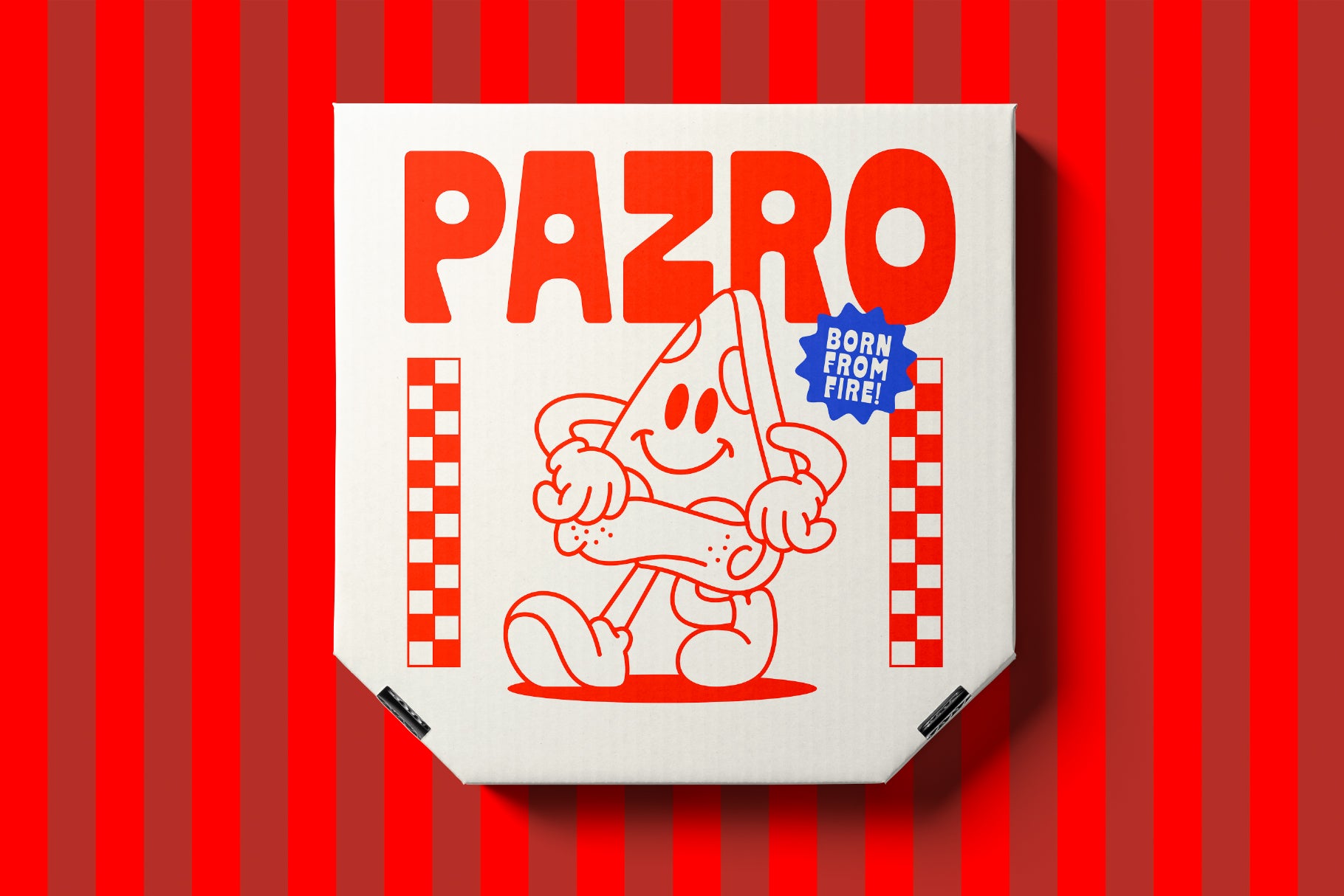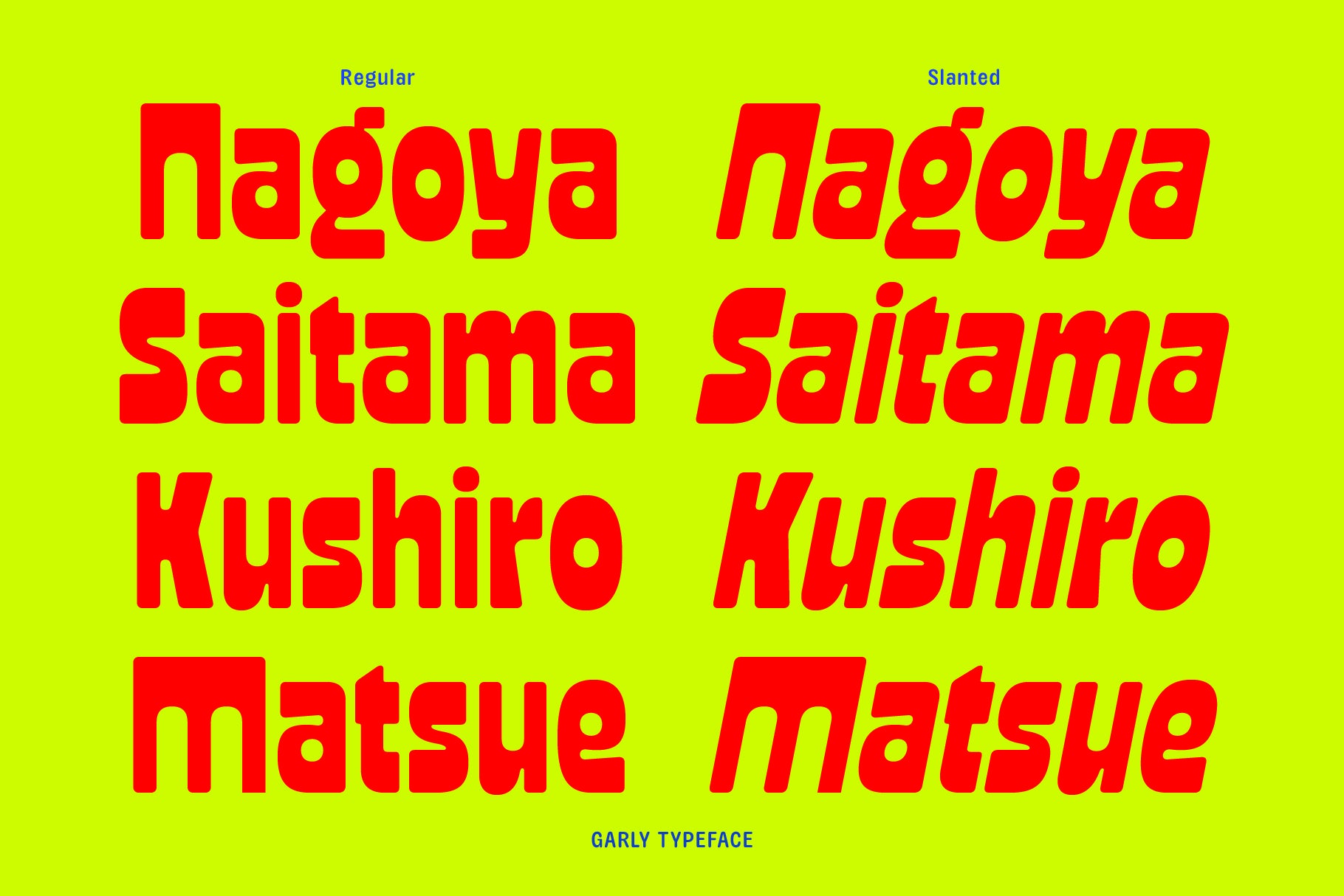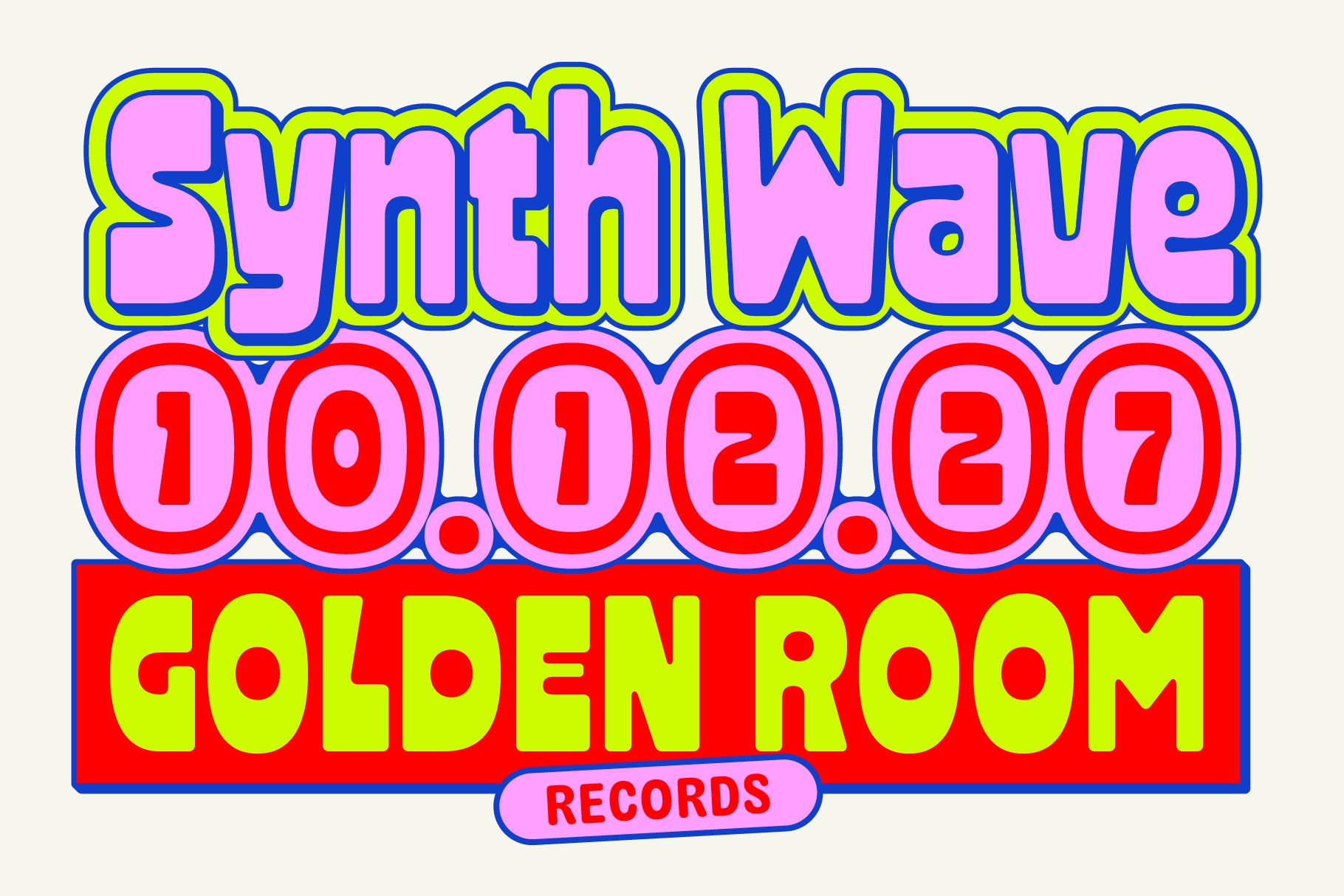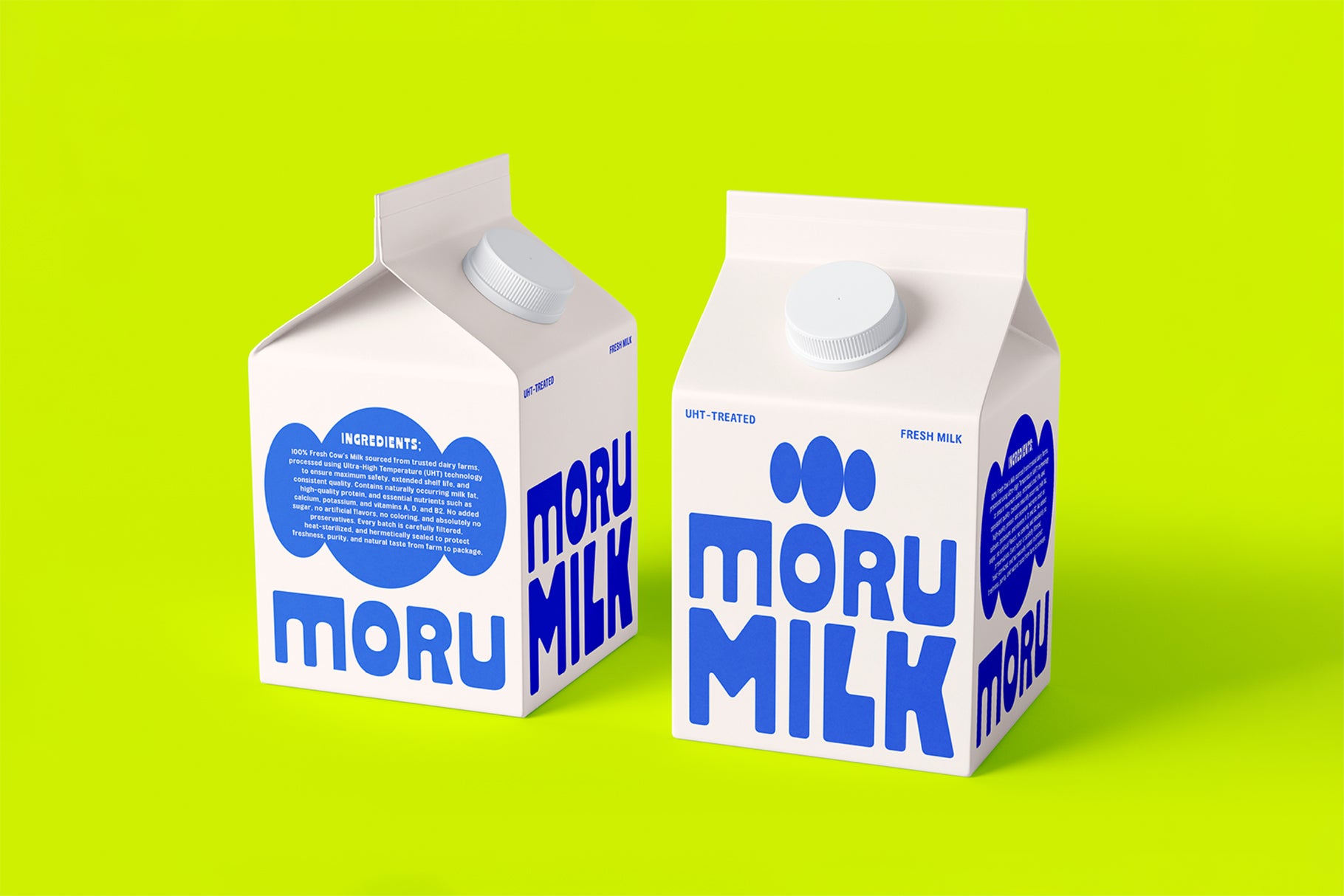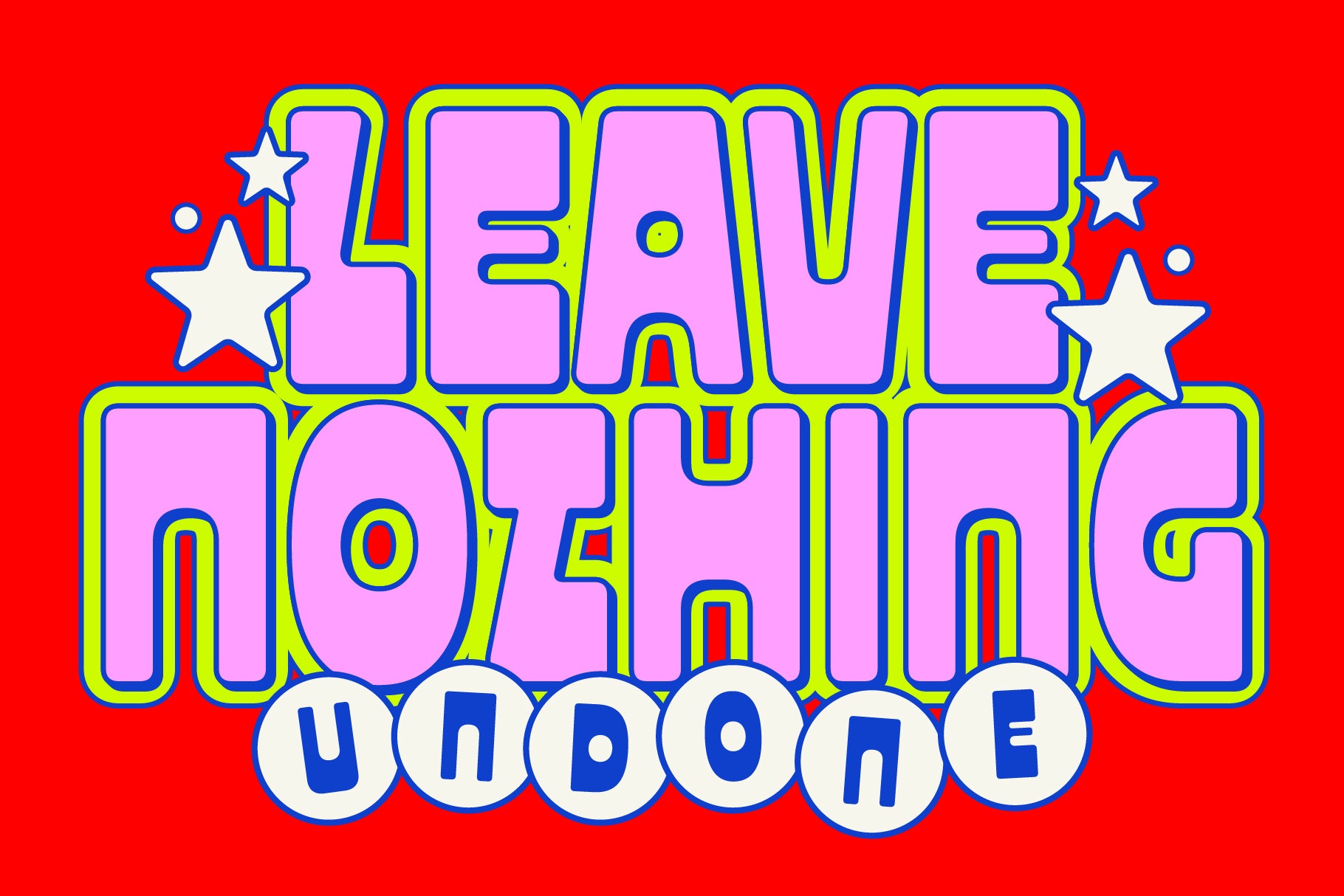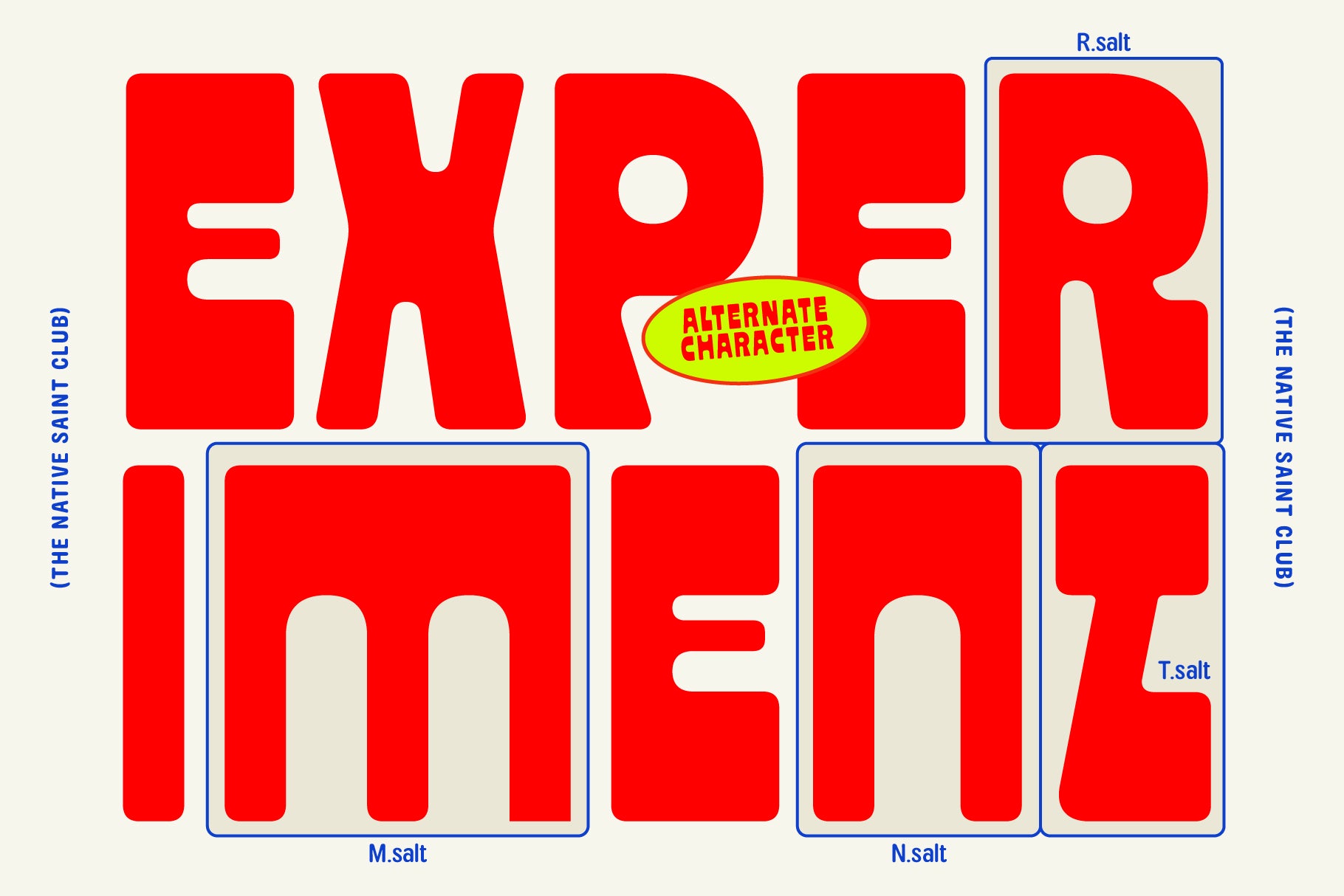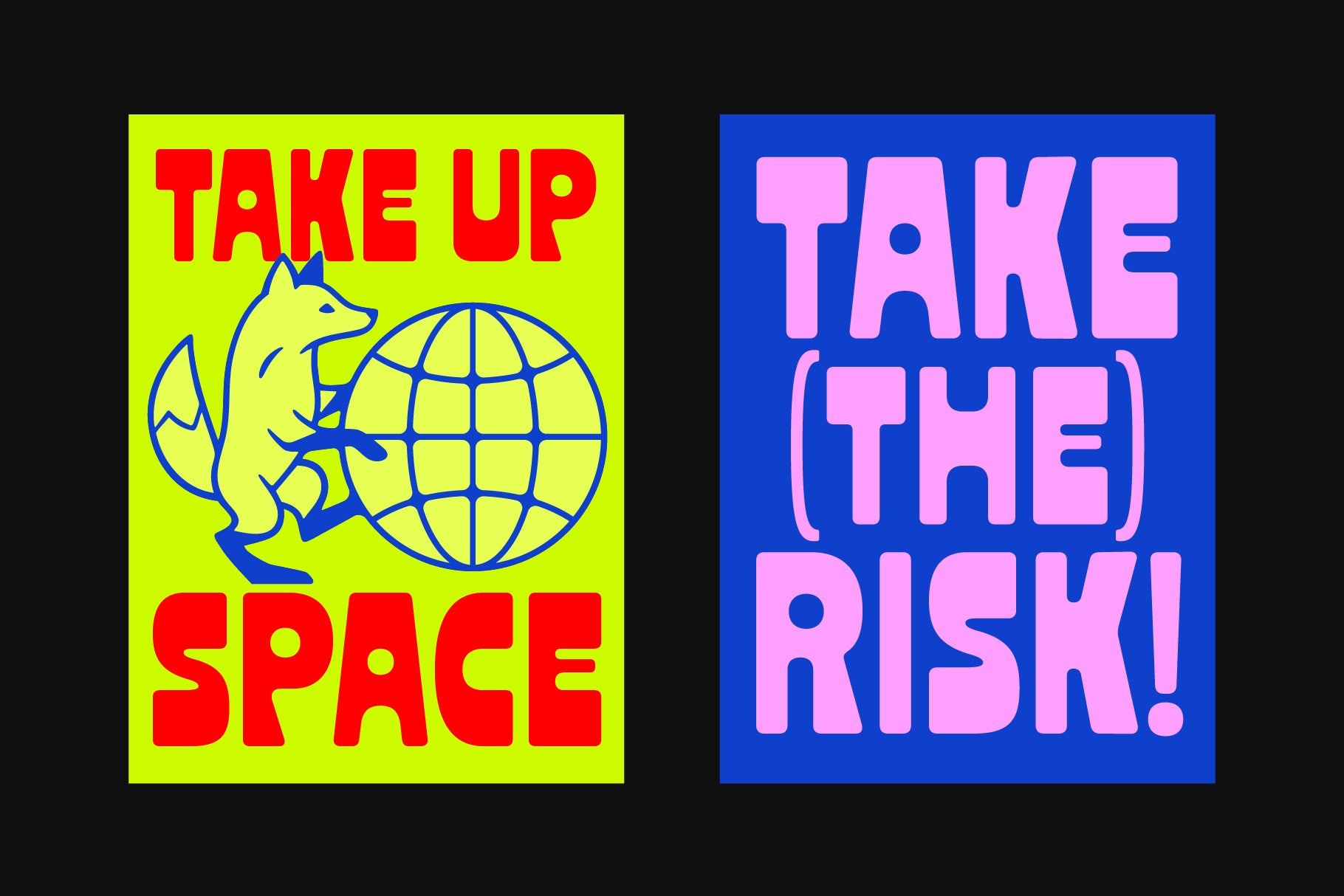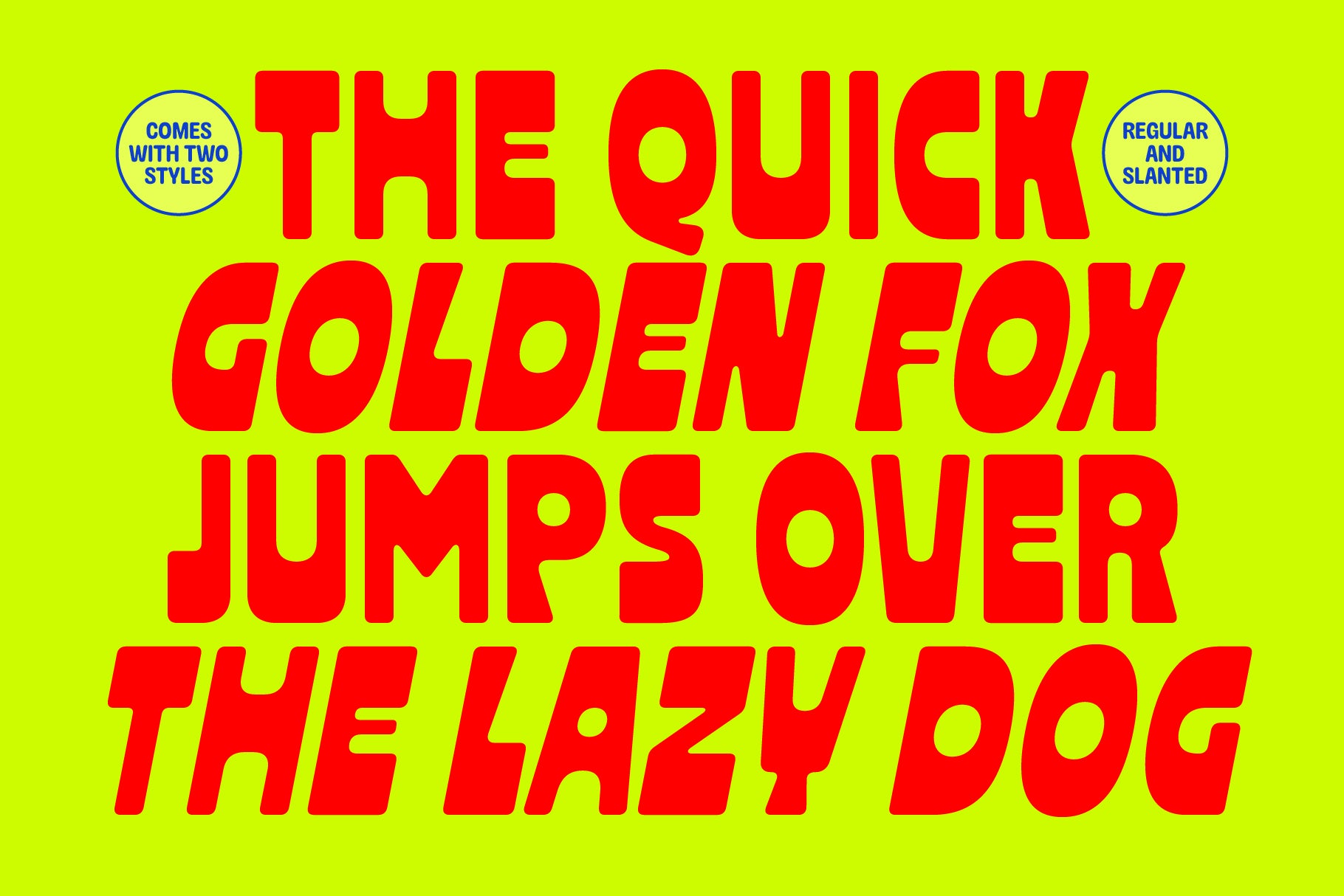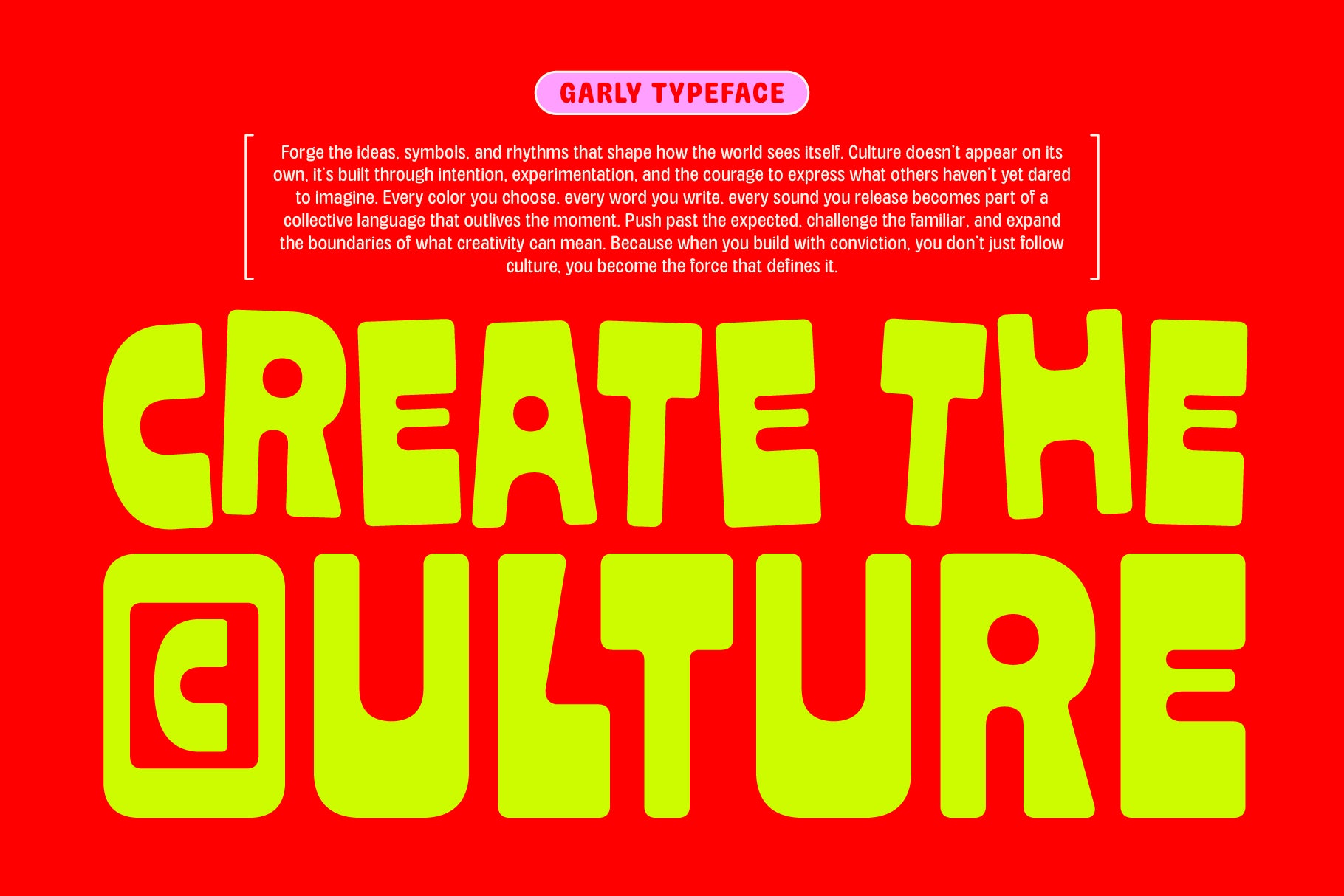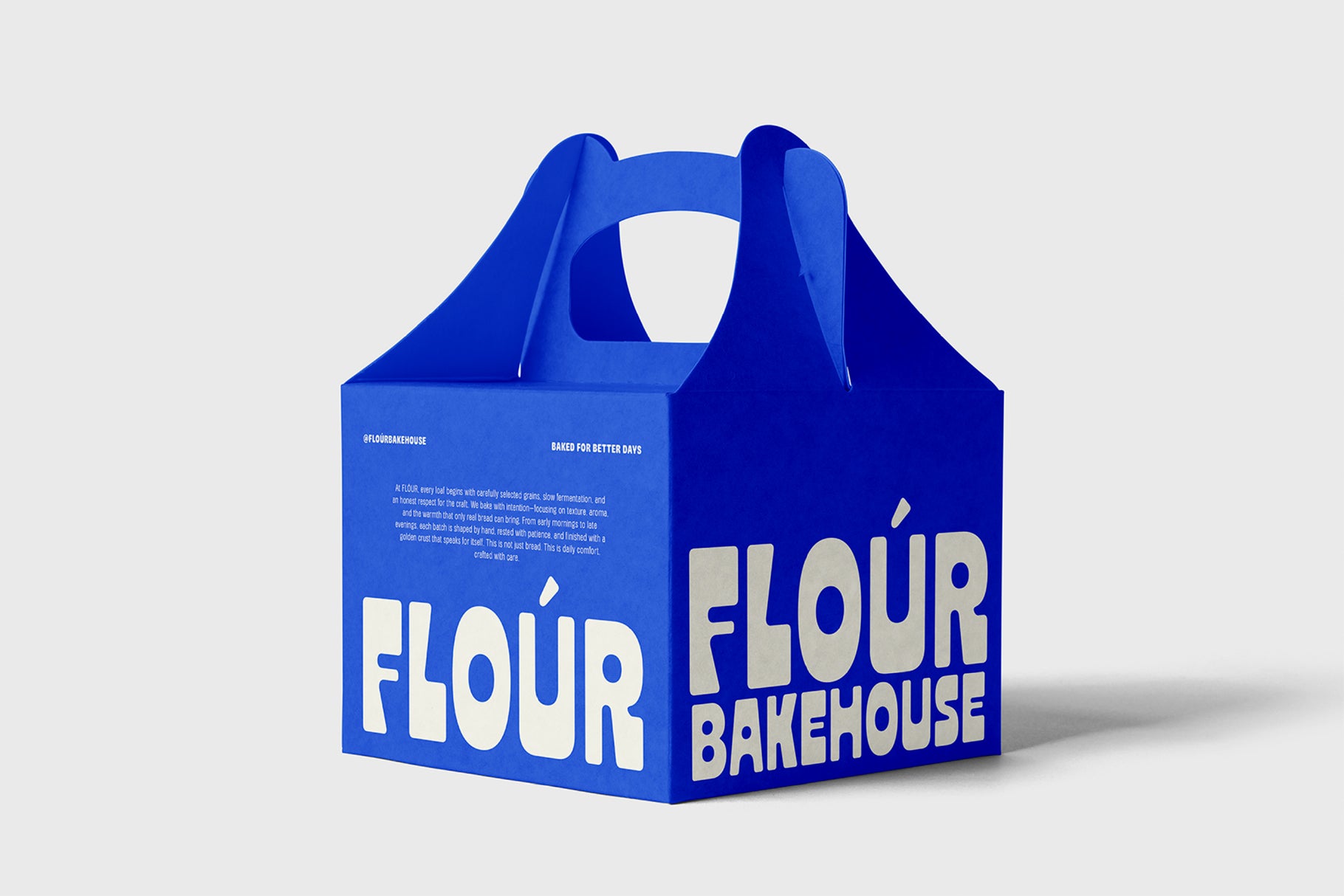
Tipografía Garly TNSC
Garly es una tipografía de exhibición audaz con formas de letras redondeadas y divertidas, creada para proyectos que necesitan calidez y presencia por igual. Como versión evolucionada de Grand Mottley Sans, ha sido refinada con bordes más suaves y formas de caracteres mejoradas para ofrecer un mejor equilibrio visual y legibilidad, conservando el carácter amigable del original a la vez que ofrece un resultado más pulido y versátil.
Moderna, cercana y adaptable a una amplia variedad de contextos de diseño, Garly se presenta en dos estilos — Regular y Slanted — para ofrecerte la flexibilidad de alternar entre lo compuesto y lo dinámico dentro de un mismo sistema visual.
Características
• 501 glifos
• 2 estilos (Regular, Slanted)
• Minúsculas
• Mayúsculas
• Diacríticos
• Ligaduras
• Números (3 conjuntos)
• Puntuación
• Símbolos
• Monedas
• Matemáticas
• Flechas